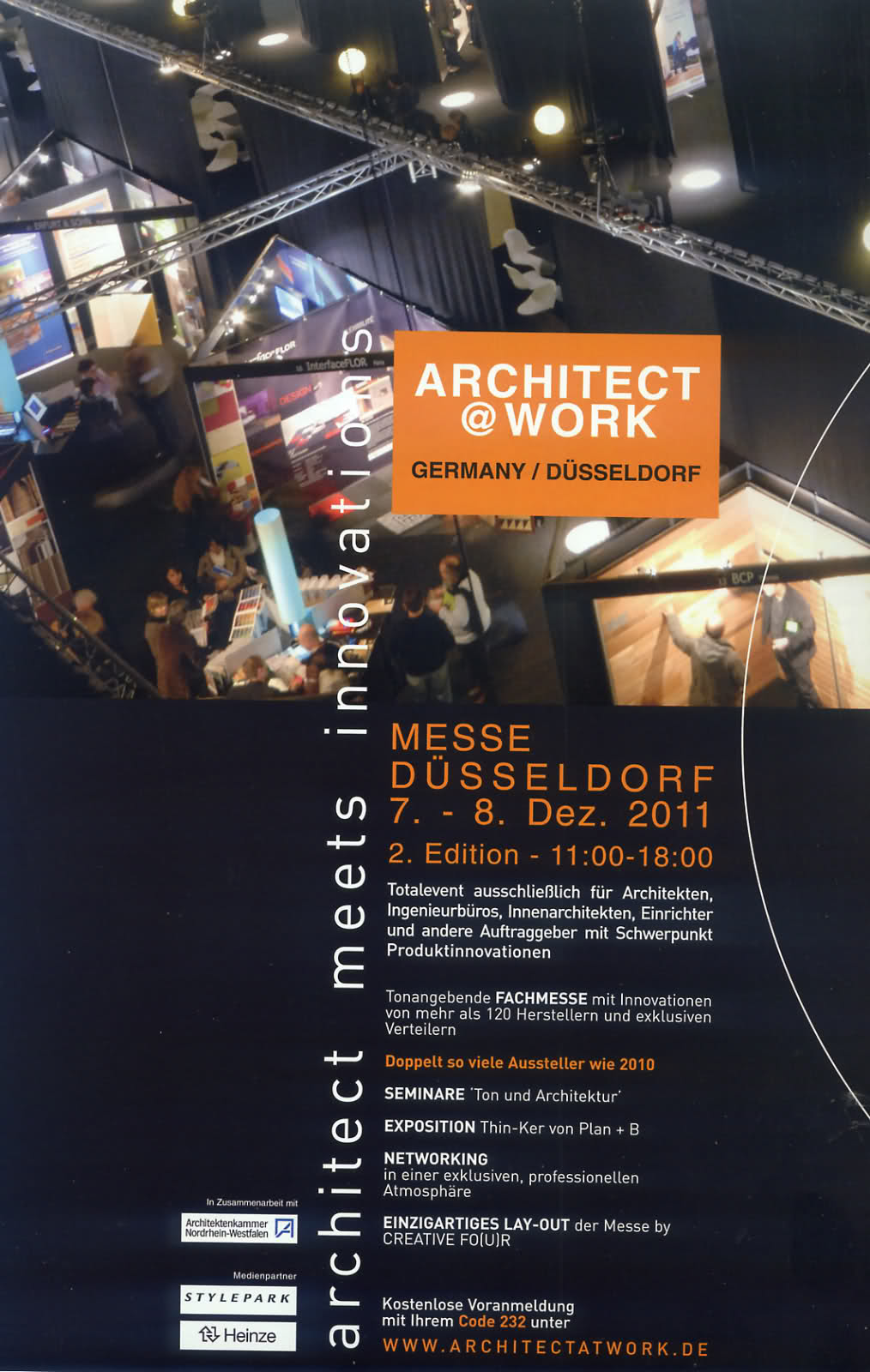
Selten eine solche schlechte Anzeige gesehen
wie der Titel schon sagt und das in einer wirklich teueren Fachzeitschrift.
Da wird einem ja nur vom Hinsehen schwindelig. Das sieht aus, als fiele man zusammen mit dem Text gleich auf die Stände und Menschen. :shock:
Das wäre ein Beispiel aus dem echten Leben für die Kollegin, die hier vor einer Weile mal Hilfe gesucht hat bei der Erstellung eines Lehrplakates zum Thema »schlimme Typoschnitzer«. ;-)
Gerade sehe ich erst das „einzigartige Lay-Out der Messe“! :lol:
Das ist korrrrekt. Fast.
Lay-out, Lay|out [:'|, auch ':...], das; -s, -s <engl.> (Druckw. Text- und Bildgestaltung)
Ob die kreativen Vier auch für die Anzeige verantwortlich zu machen sind? Das wäre dann ja ein ganz schönes Eigenlob … oder auch -tor. ;-)